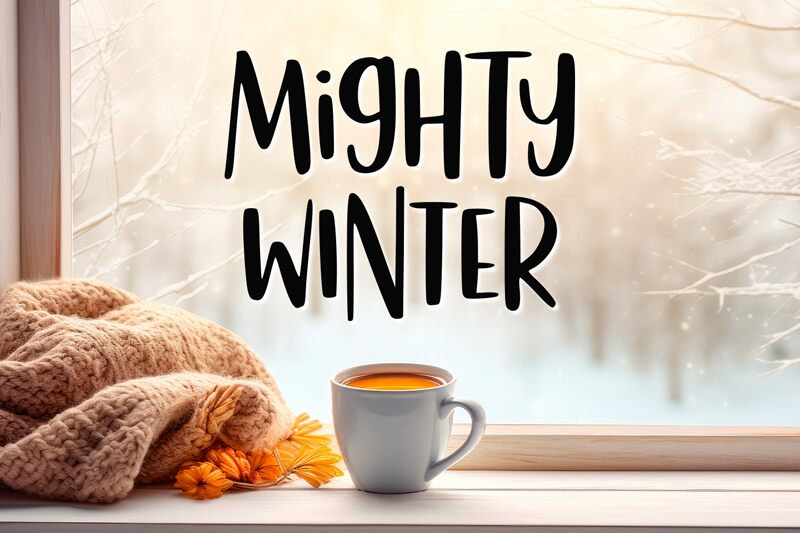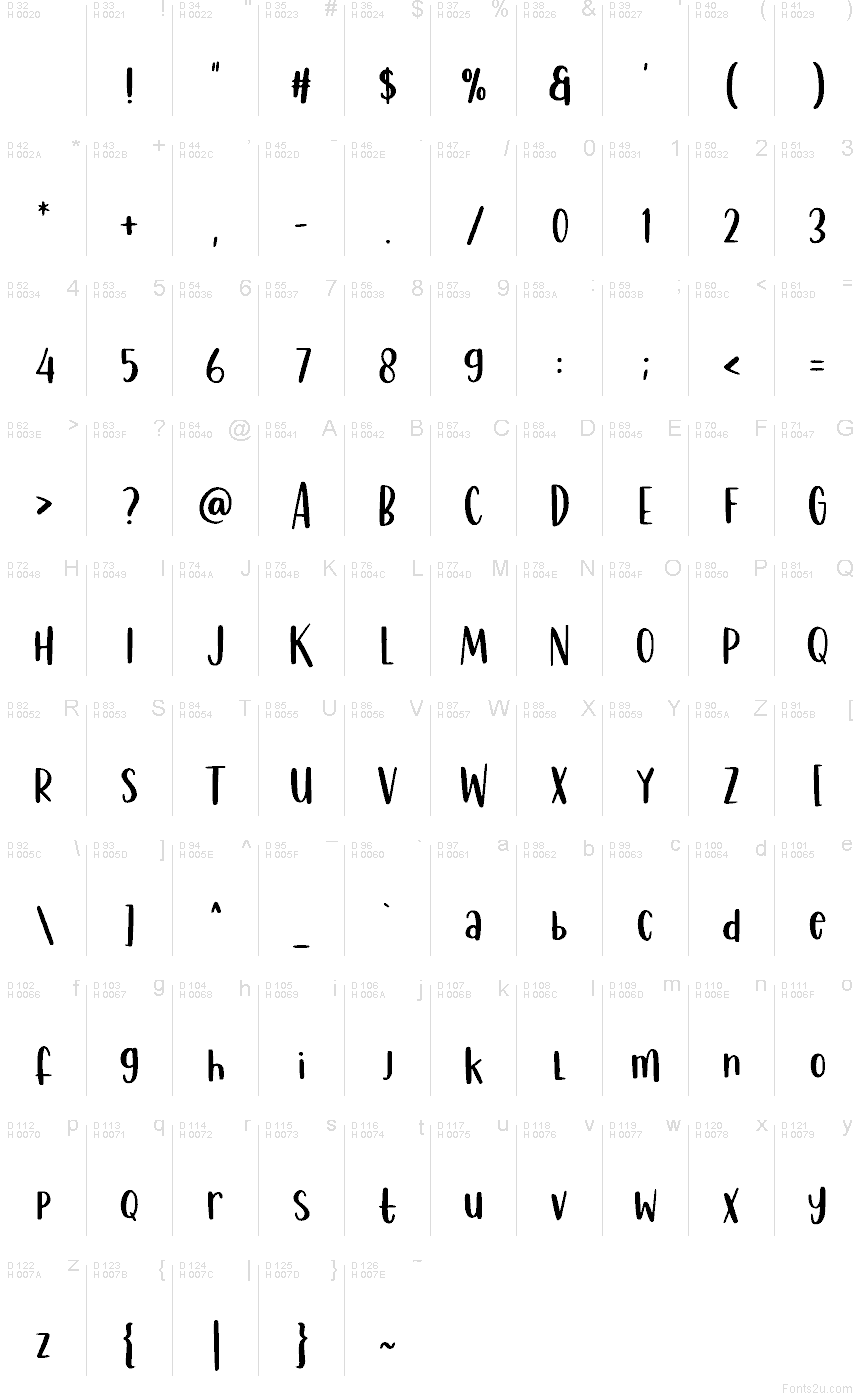
Mighty Winter, creata da Panggah di Abo Daniel Studio, è un font brush gratuito che sembra tracciato in un solo respiro deciso, con quel tocco leggermente traballante. I tratti sono spessi e carichi di inchiostro, con spazi vivaci e un ritmo saltellante che conferisce un aspetto amichevole e fatto a mano, senza risultare mai disordinato. C’è un’energia accogliente nel modo in cui le lettere rimbalzano, come una nota invernale scritta di fretta su carta kraft con un pennarello ben carico.
Mighty Winter è perfetta per promozioni natalizie, lavagne da bar, set di sticker, inviti per feste di bambini, miniature per YouTube, grafiche per abbigliamento confortevole e brevi titoli su packaging. Usala in dimensioni medie o grandi per mantenere nitida la sua texture ricca e abbinala a un font sans serif geometrico e pulito per i testi di supporto. Questo font gratuito aggiunge personalità immediata quando cerchi qualcosa di casual, audace e autentico.